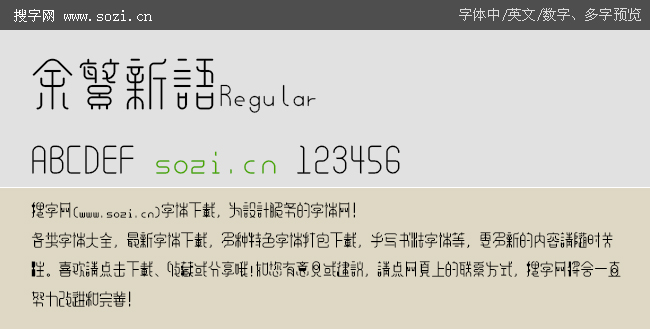
余繁新語(yǔ)-Regular
搜字網(wǎng)給大家提供一款余繁新語(yǔ)-Regular中文字體下載,余繁新語(yǔ)是字體作者余繁設(shè)計(jì)的一款小篆簡(jiǎn)化中文字體,既新潮又古典,提供4種字重可供選擇,余繁新語(yǔ)采用MIT許可(可免費(fèi)商用)授權(quán)發(fā)布,感謝作者的分享。
- 風(fēng)格類別: 篆書(shū)